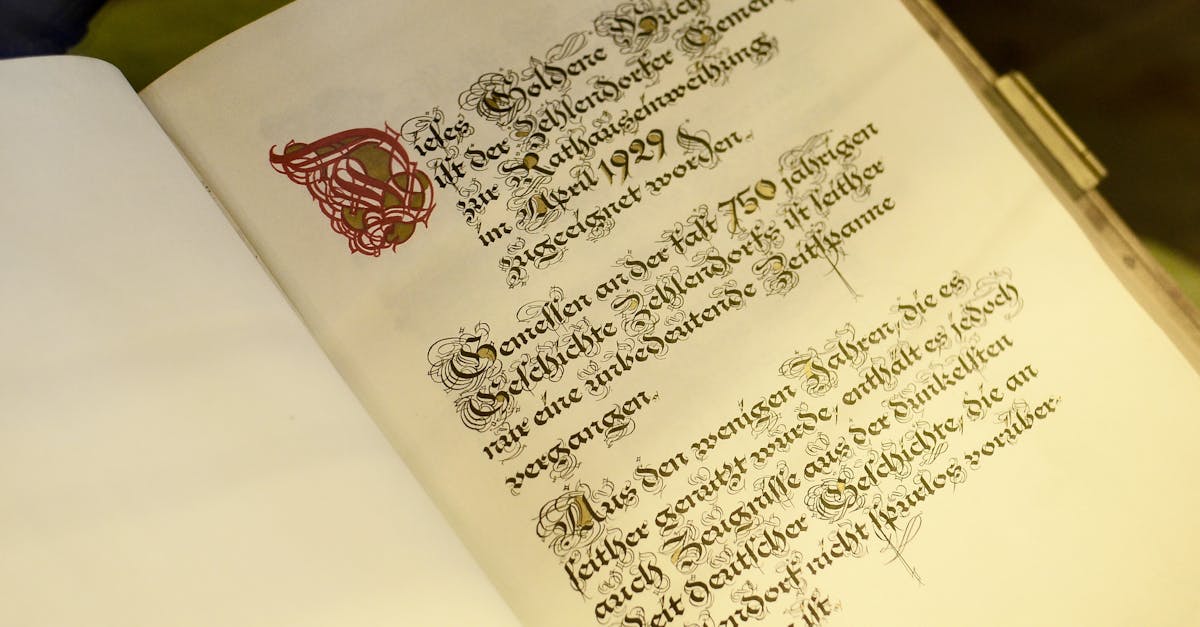
Analyse : les typographies gothiques dans les journaux anciens
Il suffit d’une page jaunie, d’une encre un peu fanée pour sentir palpiter sous nos doigts l’écho d’un temps révolu, où chaque lettre imprimée portait le poids d’un art oublié et d’un message codé. L’univers des TypoGothique dévoile un monde fascinant où le tracé des GothicLetters n’est pas qu’une simple calligraphie, mais la chambre noire d’une époque, enveloppée d’ombres et de lumière, entre PatrimoineGraphique et récit silencieux. Ces caractères, présents dans les PressHistorique, témoignent d’une AncienneImprimerie qu’il nous faut aujourd’hui explorer, revisiter, ressentir.
Plus qu’une lecture, c’est une plongée où s’entremêlent le souffle rauque des presses lithographiques, l’histoire sociale et politique imprégnée dans la matière même du papier, et le combat de familles de typographes innovateurs qui, de génération en génération, ont su transmettre un art complexe, mêlant rigueur technique et audace esthétique. Le tout repose sur les lignes sombres, les contreformes anguleuses d’une TypographieRetro qui, loin d’être un simple vestige, resurgit avec force dans les mouvements contemporains du GothicRevival.
L’analyse ici proposée navigue à travers siècles et décors, passant des premières impressions en caractères gothiques aux décrets sombres qui ont brisé puis ravivé leur usage, pour comprendre comment, aujourd’hui, à travers les archives et les ArchivesTypographiques, ils continuent de fasciner, d’inspirer, et parfois de troubler.
Les origines et la diversité des typographies gothiques dans les journaux anciens
Il serait vain de réduire les TypoGothique à une unique forme figée dans la pierre. Sous l’épais voile des siècles médiévaux jusqu’à la Renaissance, cette famille de caractères se déploie dans une incroyable variété de styles, chacun semblant murmurer un dialecte graphique propre à son territoire, son époque, et son contexte politique. Ces écritures, issues des manuscrits de la fin du Moyen Âge, traduisent une rigueur du trait et une esthétique sombre, souvent qualifiée d’ÉcrituresDélabrées à cause de leur complexité et de leur rare lisibilité immédiate.
Parmi les déclinaisons majeures, les caractères allemands comme le Schwabacher et le Fraktur se distinguent. Le premier, née entre 1480 et 1530, porte en lui une charge symbolique profonde : il devient emblematique d’une résistance, celle contre la domination papale, embrassée par une noblesse en conflit avec l’humanisme renaissant des pays voisins. Le Fraktur, adopté plus tard au XVIe siècle, incarne une évolution vers plus de clarté, notamment à la cour de Maximilien Ier.
La Réforme protestante trouve dans ces caractères un prolongement graphique de ses idées. La manière dont ces polices servent une cause montre l’intersection indissociable entre esthétique typographique et idéologie. Cette dimension politique explique également l’évolution fluctuante de ces styles, bouleversée par les aléas des pouvoirs successifs, et notamment par les décrets du XXe siècle.
Ce tableau succinct présente les grandes familles de caractères gothiques dans les journaux anciens, leurs caractéristiques symboliques et historiques :
| Typographie | Époque | Origine Régionale | Caractéristiques | Symbolisme |
|---|---|---|---|---|
| Schwabacher | 1480-1530 | Allemagne | Traits anguleux, formes arrondies, complexité | Résistance papale et noblesse anti-humaniste |
| Fraktur | 16e siècle | Cour de Maximilien Ier (Allemagne) | Plus lisible, formes brisées claires | Identité allemande et diffusion de la Réforme |
Au-delà de l’Allemagne, le terme « gothique » désigne en France un ensemble de caractères propre à la typographie médiévale. Mais il triomphe moins longtemps : dès le début du XVIe siècle, les imprimeurs français abandonnent progressivement ces polices au profit des lettres romaines et italiques, que l’on jugera plus élégantes, plus fluides. Ce passage structure le paysage graphique, modifiant indéfectiblement la manière dont est perçue la lecture elle-même, partant d’un art presque mystique vers une forme rationnelle et classique.
L’intérêt contemporain porté à la TypographieRetro gothique est la preuve vivante de cette tension entre mémoire et modernité. Explorer cet univers, notamment dans le cadre des expositions comme celle proposée dans cette manifestation dédiée à l’esthétique gothique, offre un aperçu des mécanismes complexes qui ont sculpté notre rapport à la lettre imprimée et au récit graphique.
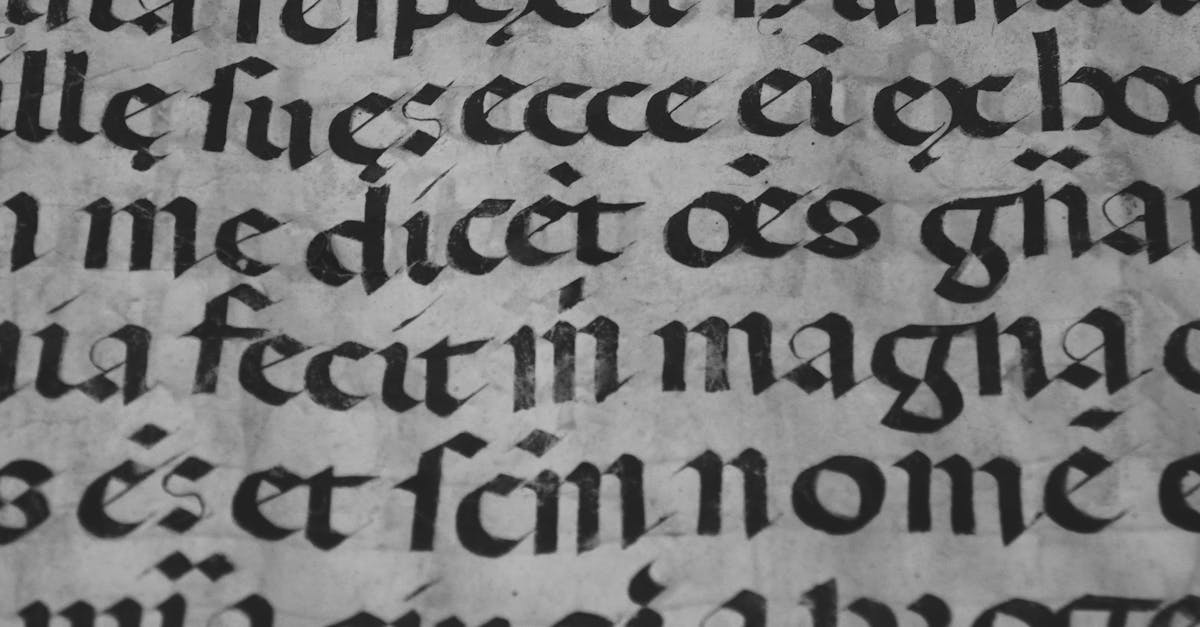
La transmission typographique à travers les dynasties de typographes : une science et un art
La survie et l’évolution des caractères gothiques dans les journaux anciens ne s’expliquent pas seulement par des tendances esthétiques ou idéologiques, mais aussi par la force des dynasties typographiques qui se sont perpétuées à travers les siècles. Le cas de la famille Didot est emblématique de cette transmission dans la haute sphère de l’imprimerie et de la typographie en Europe.
Pierre François Didot, héritier de cette lignée, illustre parfaitement comment une maison réputée jusqu’au XIXe siècle mêlait tradition, innovation technique et sens aigu du détail. Il a ainsi conçu l’un des premiers codes typographiques destinés aux correcteurs, un outil destiné à assurer la rigueur d’impression dans un univers où chaque caractère devait obéir à une esthétique aussi rigoureuse que fonctionnelle.
Le savoir-faire accumulé dans la lignée des Didot inclut des innovations cruciales en matière de qualité du papier, de finesse des traits et d’équilibre des blancs et des noirs, donnant naissance à ce que nous pourrions appeler aujourd’hui une forme d’élégance graphique sombre, à la fois classique et mystérieuse. Cette alliance de précision et d’expressivité correspond parfaitement à l’esprit du GothicRevival, qui puise dans les anciens caractères non seulement leur forme, mais aussi leur charge émotionnelle et leur profondeur historique.
La table suivante résume quelques-unes des contributions majeures des DIdot à la typographie :
| Génération Didot | Apport Principal | Influence sur la Typographie | Impact dans l’imprimerie |
|---|---|---|---|
| François Didot (1713-1785) | Technique du coup-d’œil et qualité du papier | Standardisation et clarté dans l’impression | Amélioration notable de la qualité d’édition |
| Pierre François Didot (1731-1795) | Premier code pour correcteurs typographiques | Rigueur et contrôle de la qualité | Fiabilité accrue dans la presse imprimée |
| Didot aîné et descendants | Innovations en typographie et papeterie | Évolution vers une esthétique sobre et sombre | Harmonisation entre art et technique |
Cet engagement intergénérationnel manifeste l’importance d’une sorte d’orfèvrerie graphique dont les traces, encore visibles dans les archives, sont autant de témoins d’un PatrimoineGraphique riche et complexe — un héritage qui continue à nourrir la réflexion typographique contemporaine.
Les paradoxes de l’usage des caractères gothiques dans la presse et l’imprimerie politique
Dans le labyrinthique jeu des pouvoirs et des symboles, la TypoGothique s’est souvent trouvée au cœur d’une lutte, tantôt soutien d’une cause, tantôt objet d’exclusion. La complexité esthétique de ces écritures allait de pair avec leur charge idéologique, instaurant une valeur mémorielle mais aussi polémique.
L’exemple le plus frappant se manifeste au XXe siècle, où un décret daté du 7 septembre 1934 impose aux institutions allemandes l’usage des caractères Schwabacher et Fraktur, en un geste chargé de nationalisme graphique. L’intention est alors nette : conférer à l’écriture officielle une signature visuelle distincte, fortement ancrée dans ce qu’on imagine être l’identité allemande profonde.
Mais le destin allait réécrire brutalement ce choix. L’ordonnance de Martin Bormann, signée en 1941, interdit soudain ces polices, les assimilant à un « caractère juif » par analogie avec l’écriture manuscrite de la Torah, un retournement d’usage qui expose cruellement la fragilité politique des formes typographiques.
Cette oscillation entre usage et rejet révèle combien la typographie ne saurait être réduite à un simple outil. Le pouvoir graphique a traversé les tensions majeures du XXe siècle, rendant visibles les ÉcrituresDélabrées sur les plans politique, social et culturel.
Voici une liste des grandes étapes de cette histoire typographique politique :
- Émergence de Fraktur comme symbole nationaliste au XVIe siècle.
- Adoption officielle sous le Troisième Reich en 1934 pour renforcer l’identité visuelle.
- Interdiction brutale en 1941 par décret de Martin Bormann pour raisons idéologiques.
- Remplacement progressif par des caractères linéaux « bâtons » comme la Futura, reflet d’un nouveau régime graphique.
- Post-Guerre : réévaluation critique et reprise partielle dans l’art typographique contemporain.
| Date | Événement | Conséquence | Commentaire |
|---|---|---|---|
| 1934 | Décret imposant Schwabacher et Fraktur | Uniformisation visuelle allemande | Nationalisme graphique |
| 1941 | Interdiction des caractères gothiques | Renversement idéologique | Association avec écriture de la Torah |
| 1945 et après | Adoption des linéales bâtons | Modernisation et rupture | Futura devient symbole de la nouvelle époque |
Ce contexte lourd d’histoire rappelle à quel point le graphisme est aussi un champ de bataille, où les lettres ne sont jamais qu’un outil, mais deviennent des emblèmes traversés par une charge émotionnelle et politique. Pour s’imprégner plus avant de cette tension entre esthétique et pouvoir, l’exploration approfondie des ressources telles que cette charte graphique gothique est une lecture éclairante.
La transition des écritures gothiques vers les caractères romains et italiques en France
À rebours de l’Allemagne, la France connaît dès le XVIe siècle une mutation graphique décisive. En effet, les polices gothiques, mêmes ancrées dans le PatrimoineGraphique médiéval, cèdent progressivement la place à des caractères romains et italiques plus fluides, plus aérés, qui transforment la lecture en une expérience plus immédiate et accessible.
Cette transition, loin d’être un simple départ stylistique, reflète une évolution sociale et culturelle profonde, un désir d’une modernité visuelle qui accompagne les bouleversements humanistes. L’imprimerie se veut alors porteuse d’une clarté nouvelle, supposée émanciper la lettre de ses attaches ancestrales pour mieux la projeter vers un avenir plus lisible, plus démocratique.
Cependant, bien que les gothiques périssent en grande partie dans la presse française, leur ombre persiste. SérifSombre et contrastes forts restent des héritages transmis aux caractères contemporains, nourrissant un nouveau langage graphique qui ne renie jamais ses racines funèbres.
Voici un aperçu des caractéristiques comparées entre les typographies gothiques et les caractères romains dans l’imprimerie française :
| Caractéristiques | Typographie gothique | Caractères romains et italiques |
|---|---|---|
| Épaisseur des traits | Traits épais et noirs, marqués | Épaisseur variable, avec contrastes modérés |
| Formes des lettres | Anguleuses, brisées, compactes | Arrondies, ouvertes, fluides |
| Lisibilité | Complexe, difficile à déchiffrer rapidement | Clair, facilité de lecture |
| Symbolisme | Historique, religieux, politique | Universel, culturellement neutre |
Pour ceux qui souhaitent approfondir cette mutation graphique dans un cadre esthétique et rigoureux, la lecture de ressources consacrées à la cohérence visuelle dans l’univers gothique offre un angle d’analyse passionnant.
Archives typographiques et préservation du patrimoine graphique gothique
À l’heure où le numérique tend à gommer l’empreinte physique des choses, les ArchivesTypographiques jouent un rôle primordial dans la conservation de ce trésor typographique qu’est la TypoGothique. Nombreuses sont les institutions qui veillent à la restauration et à la mise en valeur des journaux anciens, imprimés dans ces caractères d’un autre âge, que beaucoup ne savent plus déchiffrer.
La Bibliothèque nationale de France reste un exemple emblématique, où le maniement délicat des ouvrages rares, comme l’édition de 1798 des Bucoliques, Géorgiques et l’Énéide de Virgile, imprime un nouveau souffle à la mémoire typographique. À chaque feuille, c’est un univers fait de sensations visuelles troublantes qui s’offre au regard, un monde où les contrastes de l’encre forment autant de paysages d’ombres et de lumières.
- Conservation physique : préservation du papier ancien fragile
- Numérisation : accès élargi aux textes et aux typographies
- Études et recherches : analyse de la technique et du style
- Transmission : formations et ateliers dédiés aux typographes
Ces efforts conjoints permettent d’éviter que les ÉcrituresDélabrées, fragiles et précieuses, ne tombent dans l’oubli. Ils nourrissent l’énergie du GothicRevival, qui, en invitant à des expositions et manifestations artistiques, maintient vivante une esthétique séculaire, vibrante et troublante.
| Action | Objectif | Résultat attendu |
|---|---|---|
| Conservation physique | Limiter la dégradation des ouvrages | Maintenir la lisibilité et l’intégrité du document |
| Numérisation | Faciliter l’accès mondial aux archives | Diffusion accrue et études facilitées |
| Recherche | Comprendre l’évolution des styles | Documentation et enseignement |
Se détourner de ces archives aujourd’hui, ce serait refuser un chapitre entier de notre histoire graphique, et l’âpre poésie contenue dans la finesse des lignes noires. Plonger dans ces trésors du passé invite à une forme d’introspection esthétique, où les échos des anciennes presses résonnent encore dans les plis du papier.
L’influence moderne et la renaissance de la typographie gothique dans l’art et le design
La réhabilitation de ces caractères sombres ne passe plus seulement par le musée ou la bibliothèque : l’art contemporain et le design graphique explorent aujourd’hui cet univers avec la vitalité et la liberté propres aux temps modernes. Le GothicRevival traverse désormais la frontière du passé et du présent, s’inscrivant dans des créations hybrides où l’ancien dialogue avec le nouveau.
Ainsi, les créateurs contemporains reconsidèrent les trames gothiques, jouant avec les lourdeurs d’une esthétique SérifSombre, mêlant minimalisme et extravagant. Des affiches, des pochettes d’albums, et des mises en pages numériques font revivre ces formes brisées, dans un hommage vibrant et revendiqué.
- Réutilisation dans la typographie numérique pour sites et interfaces
- Artistes graphiques inspirés par l’AncienneImprimerie et le PressHistorique
- Explorations hybrides entre calligraphie et typographie contemporaine
- Mouvement de cohérence esthétique revendiquée dans l’univers gothique
Pour qui souhaite comprendre les mécanismes de cette fusion graphique, il est utile de consulter des chartes visuelles qui accompagnent la création typographique moderne, tel ce travail sur la cohérence gothique qui éclaire l’usage adapté des structures anciennes à des contextes actuels.
Techniques et outils de fabrication dans l’ancienne imprimerie gothique
Le fait de poser son regard sur les TypoGothique s’accompagne de la découverte de méthodes artisanales et mécaniques qui façonnaient chacun de ces caractères. L’ancienne imprimerie fonctionne autour d’outils précis où la plume rigide à bout carré s’impose comme l’instrument primordial pour dessiner les lettres anguleuses, témoins de l’esthétique médiévale.
Cette technique calligraphique impose rigueur et discipline, conditions nécessaires pour gérer les contours épais et les noirs profonds qui définissent la force visuelle de la typographie gothique. L’art typographique n’est pas simplement un geste artistique mais une maîtrise technique complexe qui s’est transmise d’artisan à artisan.
- Plumes rigides à bout carré pour tracer angles précis
- Composition manuelle des caractères en plomb
- Presses à bras et à planche – impression artisanale
- Techniques de gravure sur métal pour les matrices
| Outil/Technique | Fonction | Impact sur l’aspect final |
|---|---|---|
| Plume à bout carré | Création des angles et épaisseurs | Traits anguleux, noirs intenses |
| Matrices en métal gravées | Production des caractères imprimables | Précision et réplication fidèle |
| Presses à bras | Application de la pression pour impression | Qualité d’empreinte et texture |
La rigueur formelle et l’obsession du détail auraient atteint leur apogée dans certaines éditions, telles que la publication rare des « Bucoliques, Géorgiques, l’Eneïde » de Virgile (1798), où chaque lettre reflète la tension entre tradition et innovation. Ces pièces demeurent aujourd’hui des trésors d’ArchivesTypographiques, objets d’un culte discret mais profond.
Lectures et ressources pour approfondir sa connaissance des typographies gothiques anciennes
La connaissance de la TypoGothique ne s’adresse plus qu’aux seuls spécialistes des arts graphiques, mais s’ouvre à un public curieux, sensible aux richesses historiques et esthétiques. S’aventurer dans cet univers demande un retour aux sources parfois ardu, mais ô combien fascinant.
Voici une sélection non exhaustive de ressources pour s’initier et approfondir la compréhension des écritures gothiques dans leur dimension historique et contemporaine :
- Archives numériques des anciennes imprimeries et bibliothèques spécialisées
- Expositions dédiées à la typographie gothique et à son univers esthétique ici
- Manuels et guides sur les techniques de transcription et d’analyse de caractères anciens
- Articles spécialisés sur les liens entre graphisme, politique et culture visuelle
- Forums et communautés en ligne axés sur la passion pour l’AncienneImprimerie et la typographie rétro
Ces propositions s’accompagnent souvent de travaux pratiques et d’échanges culturels, nécessaires pour comprendre la puissance discrète et l’étrangeté de ces polices, bien loin des formes anodines du texte imprimé moderne. L’aventure commence donc par une immersion contemplative et critique, encourageant à percevoir les signes graphiques comme des témoins vivants, vibrants dans leur obscurité.
Pourquoi la typographie gothique fascine-t-elle encore en 2025 ?
Alors que le monde digital, synthétique et immatériel semble s’imposer en maître, la persistance et la résurgence des formes anciennes, des TypoGothique, pose une énigme profonde. Comment expliquer l’attrait que portent ces écritures SérifSombre, ces lettres aux lignes marquées, anguleuses, presque sévères, à une époque où la fluidité et la lisibilité numérique priment ?
La réponse réside peut-être dans la quête d’authenticité, dans ce retour aux textures, à la matérialité, aux imperfections d’un travail manuel et artisanal qui participe d’une esthétique funèbre et romantique, chère aux sensibilités d’un public en quête d’histoire et de sens. Dans ce contexte, la TypographieRetro se fait signe d’une résistance silencieuse face à l’homogénéisation visuelle.
Cette fascination s’incarne aujourd’hui dans des initiatives culturelles, des projets artistiques et des publications qui explorent la force évocatrice et mystérieuse de ces caractères. Ils deviennent marqueurs d’une identité singulière, d’une profondeur où pèsent à la fois le poids du passé et la vitalité du présent.
- Volonté de renouer avec un PatrimoineGraphique authentique
- Besoin de matérialité face au monde virtuel
- Attrait pour une esthétique sombre, complexe, à la fois historique et actuelle
- Recherche d’une cohérence visuelle revendiquée dans les expressions artistiques
- Revitalisation artistique par le GothicRevival
Ce phénomène s’inscrit pleinement dans une pertinence contemporaine vibrante, où la typographie devient miroir d’un état d’âme collectif, reflet d’une époque aux tensions multiples. Pour approfondir la cohérence de ce mouvement, il est possible de s’inspirer de travaux comme ce guide sur la cohérence visuelle dans l’univers gothique, source rare d’éclairage et d’analyse.
FAQ sur les typographies gothiques dans les journaux anciens
- Qu’est-ce que la TypoGothique et pourquoi était-elle utilisée dans les journaux anciens ?
La TypoGothique désigne un ensemble de caractères d’écriture inspirés des manuscrits médiévaux, utilisés principalement dans les presses anciennes pour leur rigueur esthétique et leur charge symbolique. Ils conféraient aux textes un caractère officiel, religieux ou politique très marqué. - Quels sont les principaux types de caractères gothiques ?
Les plus connus sont le Schwabacher et le Fraktur, notamment en Allemagne, caractérisés par des formes anguleuses, une épaisseur marquée, et un équilibre entre lisibilité et complexité graphique. - Pourquoi les caractères gothiques ont-ils été interdits sous le régime nazi ?
En 1941, les caractères gothiques furent jugés « juifs » car ils ressemblaient à l’écriture de la Torah, ce qui conduisit à leur interdiction officielle malgré leur usage intensif quelques années auparavant. - Comment les archives typographiques permettent-elles de préserver ce patrimoine ?
Elles assurent la conservation physique, la numérisation et la diffusion des œuvres anciennes, tout en soutenant la recherche. Cela permet à la fois l’accès au public et l’inspiration pour les créateurs actuels. - Où peut-on voir aujourd’hui une renaissance de la typographie gothique ?
Elle se manifeste dans l’art contemporain, le design graphique, les expositions thématiques et les publications qui réinterprètent ces formes dans un dialogue entre passé et présent.